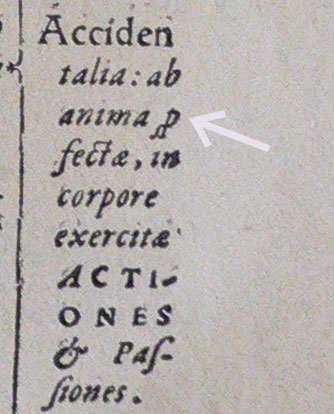
Rätselhaftes Zeichen
Bin in der Unibibliothek auf ein Buch aus dem 16. Jahrhundert gestoßen. Ein Druck, der mich schon bald zu Tränen rührt, auch wenn ich nur ziemlich mäßige Digitalfotos davon zur Verfügung habe.
Auf jeden Fall bin ich da drin auf ein Zeichen gestoßen, das ich partout nicht deuten kann. Vielleicht eine Abkürzung?
Kennt jemand dieses Zeichen?
Keine Ahnung, aber die ct-Ligatur gefällt mir :cheer:
…sieht für mich aus wie eine sehr kreative s-p-Ligatur.
hmm, das könnte eine Abkürzung/Ligatur für "per" sein.
Ich habe sowas auf Anregung eines spanisch-portugiesisch-lateinischen Linguisten in die Tierra Nueva aufgenommen. In der Vorlage sieht diese aber wie ein p aus, mit einem waagrechten Strich durch die Unterlänge durch, ist also nicht so schwungvoll.
Was ähnliches gibt es übrigens für "que" oder "qe", das sieht dann etwa so aus: q3
wobei der 3er viel viel kleiner ist und am q dranhängt.
Hübsche "ae"-Ligatur, die Unterscheidung zwischen oe und ae ist in der Kursiven ja immer ein Husarenstück ...
hmm, das könnte eine Abkürzung/Ligatur für "per" sein.
.. mich freuen auch die langen s ungemein.
In der Andron Scriptor Web gibt es das Zeichen auch. Dann müßte es Stötzner ja wissen.
das zeichen steht für die silbe ”pro”
„per” wäre ein p mit waagrecht durchkreuzter unterlänge.
Stötzner schreibt:
Es bedeutet *pro* (Schwanz nach unten); Schwanz nach oben wäre *prae*.
Eine gute Übersicht der alten lateinischen, griechischen und deutschen Schriftformen, Schreibschriften und Ligaturen findet sich auch in: Paul Arnold Grun: Leseschlüssel zu unserer alten Schrift.